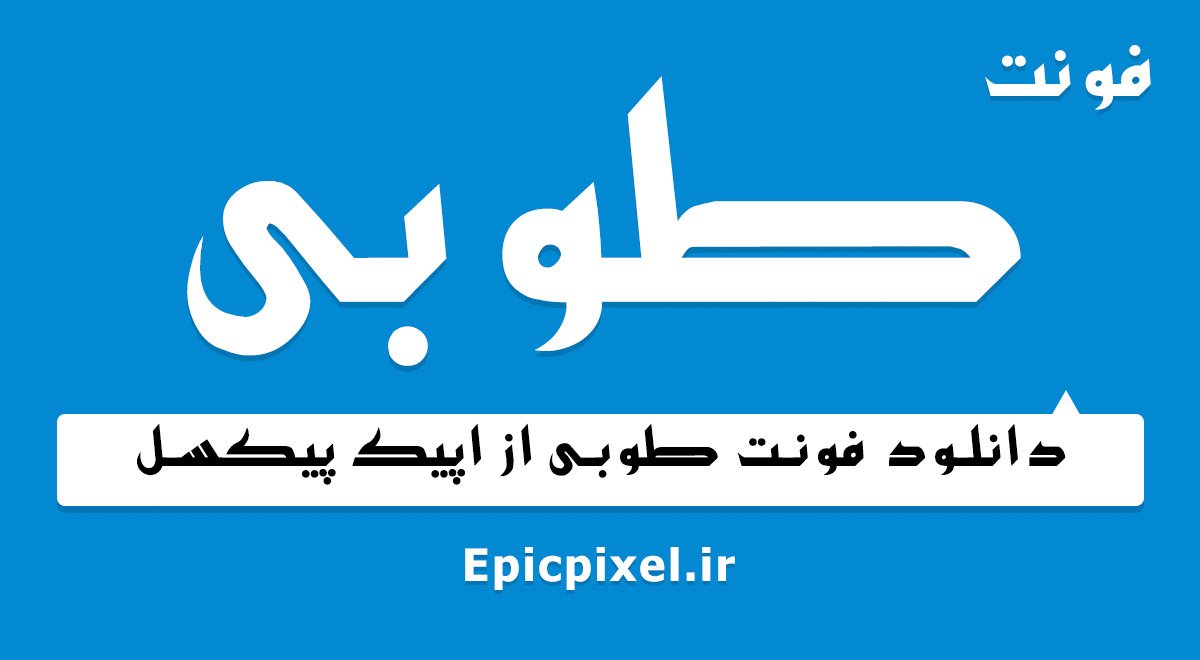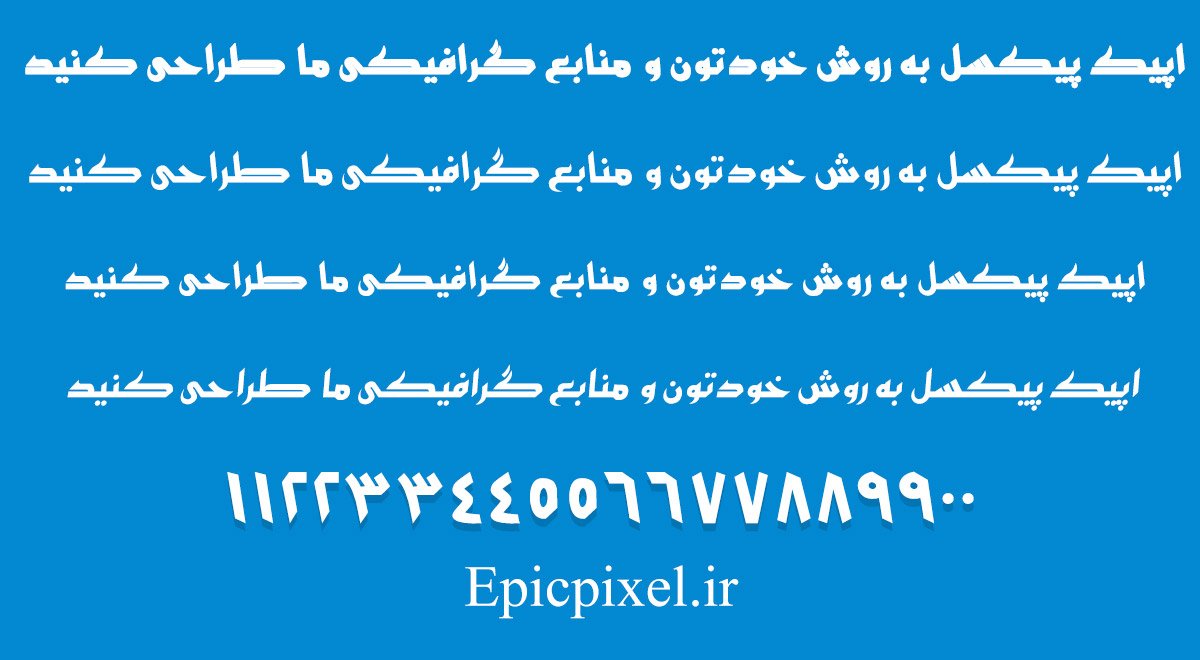
3 فونت طوبی فارسی
فونت طوبی، یک انتخاب هوشمندانه برای کسانی است که به دنبال فونتی مدرن، خوانا و کاربردی در طراحی های خود هستند. این فونت با طراحی سلیس و روان خود، خوانایی بالایی را در متون طولانی و کوتاه ارائه می دهد و به همین دلیل، گزینه ای ایده آل برای استفاده در کتاب ها، مقالات، وب سایت ها و اپلیکیشن ها به شمار می رود. یکی از ویژگی های برجسته طوبی، هماهنگی زیبای حروف فارسی و انگلیسی آن است که به طراحان اجازه می دهد به راحتی از آن در پروژه های چند زبانه استفاده کنند، بدون اینکه نگران ناهماهنگی ظاهری بین زبان ها باشند.